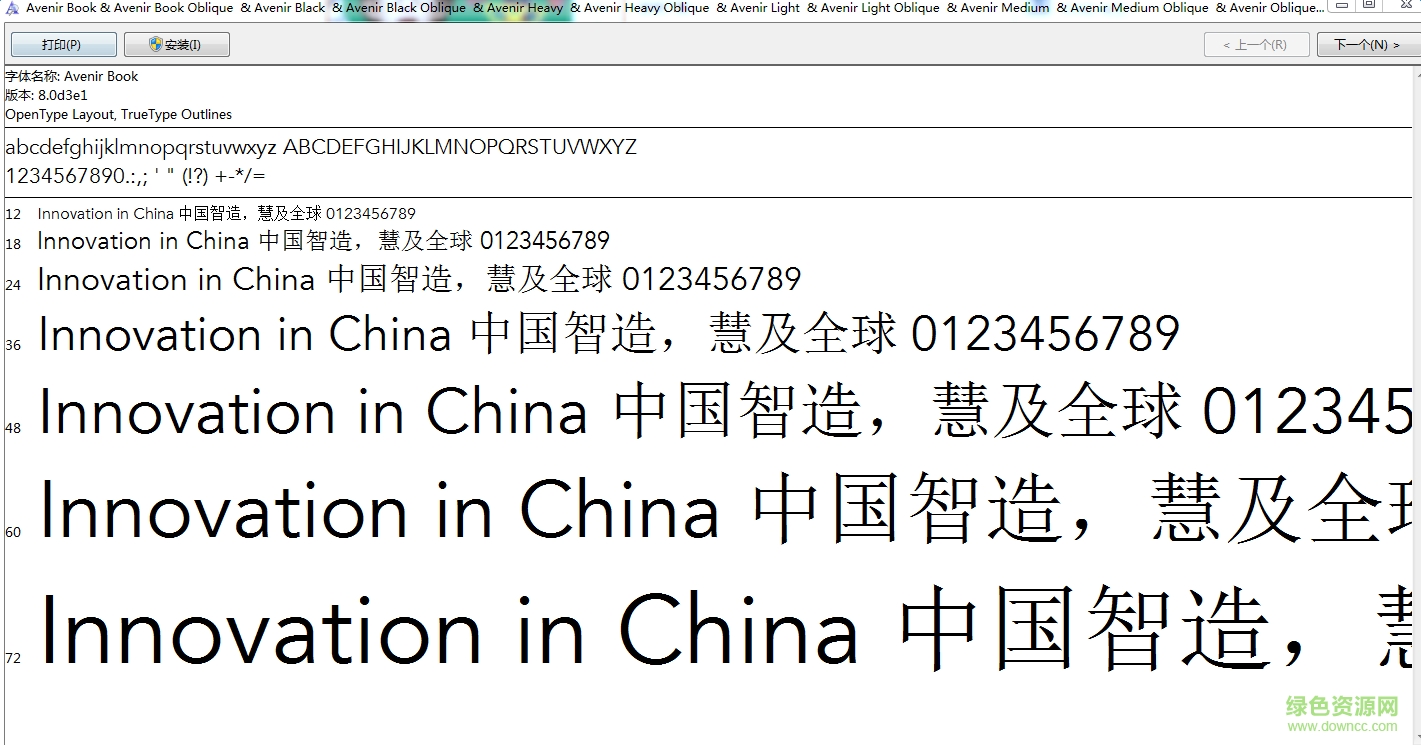
avenir book字體是一款西文字體,該字體沒有襯線裝飾,筆畫纖細,字形簡約干練,極具韻致,需要的小伙伴快來綠色資源網(wǎng)下載!
【簡與繁】
這里所說的簡與繁并不是簡體與繁體,而是筆畫細節(jié)的復(fù)雜程度。具個最簡單的例子,襯線體相對來說要比非襯線體細節(jié)復(fù)雜一些,宋體也比黑體復(fù)雜一些。正如花紋繁復(fù)華麗是古典家具的典型特征,簡潔實用的宜家家居是現(xiàn)代生活的典范一樣,字體的繁復(fù)與簡單一定程度上也代表著古典與現(xiàn)代走向。